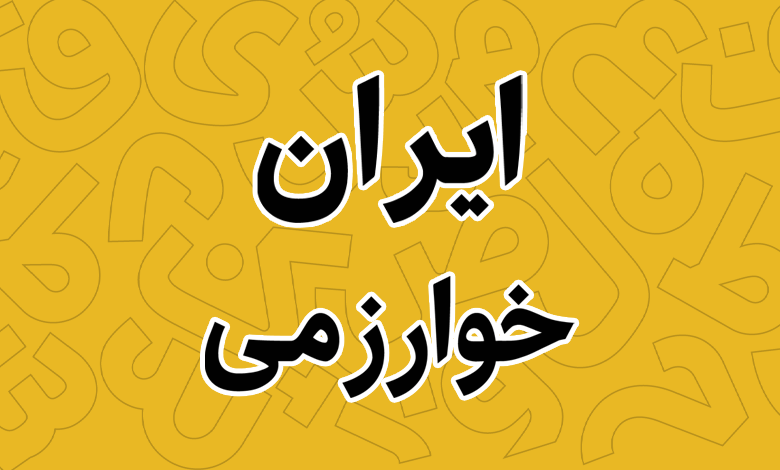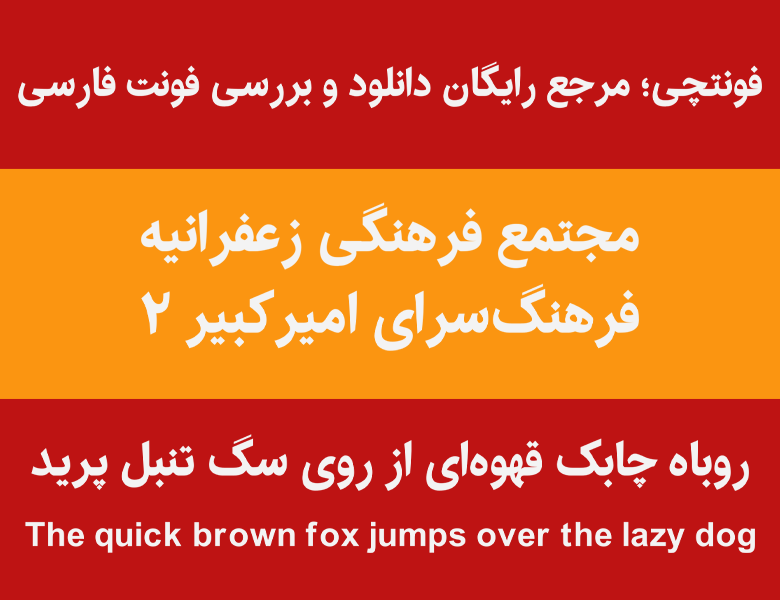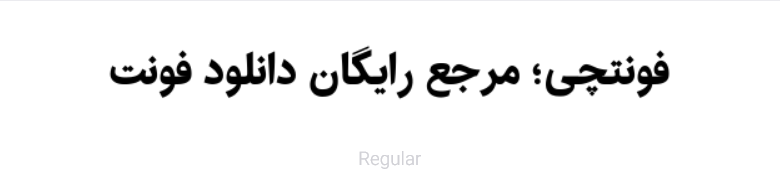
فونت ایران خوارزمی (Iran Kharazmi)
سحر خوارزمی؛ خطاط خوش ذوقی است که دارای لیسانس گرافیک است و فونت ایران خوارزمی (Iran Kharazmi) را که بیشتر با نام فونت خوارزمی شناخته می‌شود طراحی کرده است. این فونت رایگان در یک وزن معمولی (Regular) ساخته شده است که علاوه‌بر زبان فارسی، از زبان عربی همراه با اعراب کامل و زبان انگلیسی نیز پشتیبانی می‌کند. همچنین امکان استفاده از اعداد با تایپ فارسی را در این فونت دارید.
معرفی و بررسی فونت ایران خوارزمی (Iran Kharazmi)
فونت ایران خوارزمی بر پایه خانواده فونت ایران طراحی شده است. ضمن پشتیبانی کامل از زبان فارسی، از زبان عربی همراه با کلیه اعراب و زبان انگلیسی هم با ساختاری مناسب بر پایه سن‌سریف پشتیبانی می‌کند.
در نسخه بهبود یافته این فونت برای زبان عربی و سایر زبان‌های خاورمیانه‌ای، کلیه حروف و اعراب از قابلیت تکمیل گلیف برخوردار هستند. همچنین از حروف با اعداد فارسی برای زبان فارسی و حروف با اعداد عربی برای زبان عربی که در آن اعداد ۴ و ۶ متفاوت هستند فراهم شده است.
برای زبان‌های لاتین نیز پشتیبانی از زبان انگلیسی فراهم شده است که بدون نیاز به تغییر قلم می‌توانید با همان فونت خوارزمی محتوای خود را ایجاد کنید.
مزایای فونت خوارزمی
طراحی کلی این فونت به شکلی است که منحنی، شکستگی‌ها و حروف دارای ضخامت یکسان نیستند. اما تا جای ممکن سعی شده طوری ضخامت‌ها طبقه‌بندی شود که خوانایی فونت در حد ایده‌آل حفظ شود و همچنین همین ویژگی به‌عنوان نقاط ضعف و قوت در این فونت باعث بهبود رابط کاربری و خوانایی فونت گردد. برش‌های این فونت بیش از حد گرد و نوک تیز نیستند.
یکی دیگر از مزایای فونت Iran Kharazmi این است که ساختاری که برای ضخامت و وزن دادن به کلیه حروف برای آن در نظر گرفته شده، باعث شده تا در کمترین مقدار مساحت بتوان بزرگ‌ترین نوشته را با ضخامت بالا و پوشش زیاد ایجاد کرد. از همین‌رو می‌توان گفت که این فونت می‌تواند برای مطبوعات و طراحی گرافیکی گزینه مناسبی باشد.
از دیگر مزایای فونت ایران خوارزمی می‌توان به نهایت ضخامت و فشردگی اشاره کرد که در نسخه بولد شما را از برش زدن متن، تغییر جایگاه نقطه‌ها و جابه‌جا کردن حروف بی‌نیاز خواهد کرد. بنابراین اگر بخواهیم یک نگاه کلی به مزایا و ویژگی‌های این فونت داشته باشیم می‌توان به موارد زیر اشاره کرد:
• مناسب متن، مطبوعات، تبلیغات و طراحی گرافیکی
• فونت فارسی بر پایه خانواده فونت ایران و مناسب برای زبان فارسی
• هماهنگی کامل و عالی با زبان‌های عربی و انگلیسی بر پایه سن‌سریف
• پشتیبانی کامل از اعداد فارسی، عربی و انگلیسی بر پایه صفحه کلید سیستم‌عامل
• پشتیبانی کامل از اعراب گذاری در زبان‌های عربی و خاورمیانه‌ای همراه با کاراکترهای خاص
• رعایت کامل فواصل و خطوط در بخش‌های تحتانی، فوقانی و شکستگی‌های فونت که دارای منحنی و شکستگی ملایمی هستند
فونت ایران خوارزمی با توجه به وزن و ضخامتی که به متون می‌دهد می‌تواند انتخاب بسیار عالی برای سرتیترها باشد. خصوصا سرتیترهای مورد نیاز در مطبوعات، مجلات و روزنامه‌ها که باعث می‌شود ضمن افزایش خوانایی توجه کاربر را به‌خود جلب نماید.
این فونت را می‌توانید با ترکیب کردن در کنار سایر فونت‌های مناسب متن همچون ایران سنس، وزیر و ده‌ها فونت فارسی دیگر استفاده کرده و بهترین خروجی را از آن کسب نمایید.